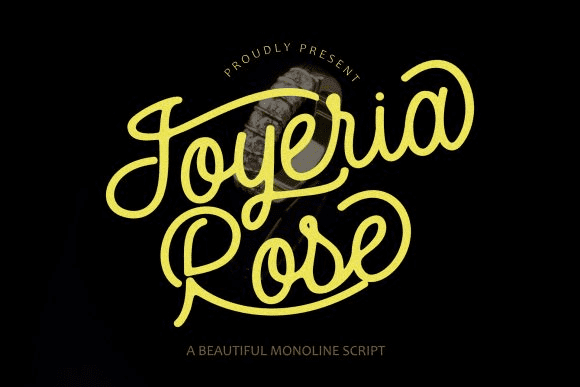
Название: Joyeria Rose Font
Joyeria - это причудливый шрифт с расслабленной темой, отличающийся прекрасным стилем.
Независимо от темы, этот шрифт будет невероятно полезным для библиотеки ваших шрифтов, так как он способен возвысить любое творение.